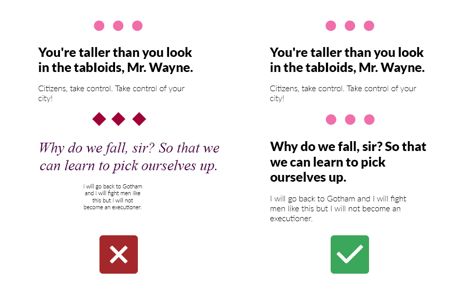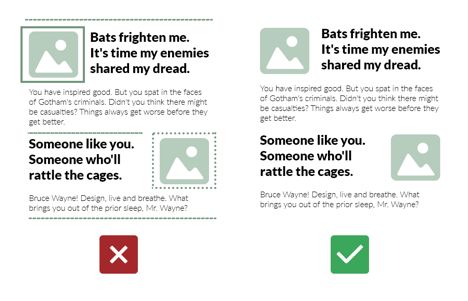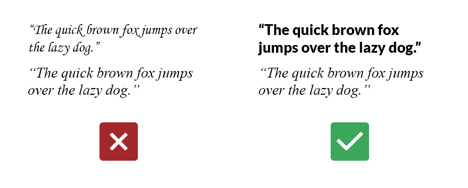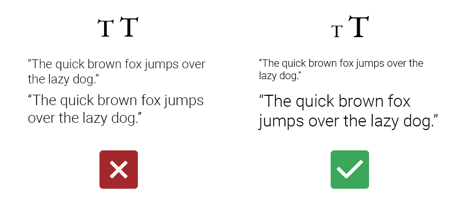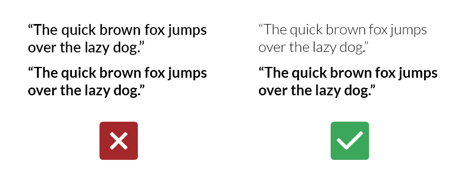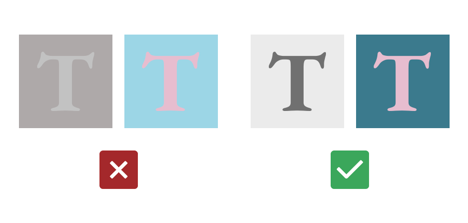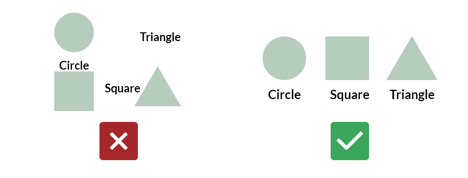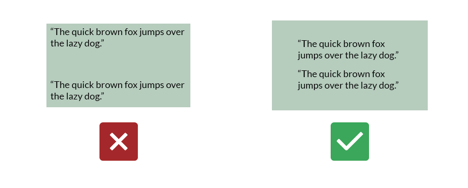
UI设计师必须知道的四大UI设计原则
这些原则来自专业设计师在日常工作中的经验积累、对作品集的分析、Facebook和ins上的设计海报、油管上的短视频等等。
很多朋友问我,怎么做才能让设计出来的东西看着会更好呢?俗话说得好“授人以鱼,不如授之以渔”,所以比起直接帮你们设计,我更愿意告诉你们一些有价值的设计原则,这样的话,当你们再遇到同类问题时,你们可以运用这些原则更好的解决问题。时间长了,我发现我一直在给设计师们重复的建议,于是我总结出了以下四个UI设计法则。
对比
♦ 确保所有元素之间有足够的对比   ♦
为什么呢?因为有些设计元素之间只有一点点不同,在差异极小的时候,很容易形成一种类似恐怖谷的感觉。看起来总是觉得不太舒服、难以理解,这肯定不是我们想要的效果,所以设计元素要么完全相同,要么明显不同。
1、颜色:
深色文字用在浅色底上,反之亦然
例:不要把浅灰色放在中灰色背景上,不要把浅粉色和浅蓝色搭配在一起;这样不仅不便观看,也很不协调
2、尺寸:
将 大小完全相同 或者 大小差异明显 的元素放在一起
例:不要把32pt和36pt的文本放在一起;18pt和36pt文本放在一起会更合适
3、字重:
尺寸相同时,要将 粗细完全相同 或者 粗细差异明显 的元素放在一起
例:不要把某种字体的粗体和黑体放在一起,因为它们看起来太相似了;细体和粗体搭配起来会更好
4、字体样式:不要把两个斜体字(或衬线体)放在一起
例:不要把“Times New Roman”和“Georgia”放在一起,因为它们看起来太像了;要搭配不同风格的字体
一致性
♦ 确保相似的元素表现形式一致  ♦
1、作品通过保持元素的一致性才能保持简洁,应该让用户把注意力集中在设计亮点上,而不是去关注那些无关紧要的东西。
2、一致性会增加用户的信任感,让作品看起来是经过精心设计的,而不是随便拼凑在一起的。(需要注意的地方有:字体,色调,网格,对齐,装饰元素、风格等等)
当你在创作系列作品时,要让它们保持风格一致,比如Youtube的视频展示图,或者Medium的文章封面,设计风格都应该保持一致。换句话说,你的作品需要有你自己的风格。
奥卡姆剃刀原理
♦ 减少视觉噪声  ♦
设计师们总是在强调少即是多。为什么呢?因为人类的大脑的容积是有限的,很难在超负荷的状态下处理信息和做决定,所以简洁的元素更适合大脑接收信息。(元素包括字体、颜色、阴影、结构、笔画、图标、图片等等)
奥卡姆剃刀原理可以应用到所有的事中。
比方说,如果只需要用2个元素就能完成某件事,就不要用3个元素;如果某件事可以用10个元素来完成,就不要用20个!
空间
♦ 事物所处的位置决定了它是否是关键  ♦
为什么位置很重要? 因为元素摆放的位置、元素周围的留白,都会影响设计的复杂性。因此,更好的位置摆放会使产品看起来更加赏心悦目,也更加易于交互。
设计中的空间使用表现在这3个方面:
1、亲密原则=相关性
与其他元素相比,彼此更接近的元素,会被认为存在更多的关联。这个原则很重要,我感觉它常常被专业的设计师忽视。
这个原则有多种实际的案例,例如:
• 行间距应该大于字间距;同样的,段落间距也应该比行间距要更大
• 设计元素之间的间距,应小于这些元素与外部边缘的间距
• 元素的相关说明信息应该位于相关的元素附近
2. 负空间
结合奥卡姆剃刀原则,尽可能的为你的设计提供负空间,使它们看起来更整齐且、意义更明显。如果将太多元素放在有限的空间内,就好像同时听三首歌一样,听到最后什么都听不到。
看看Apple的网站,人们可以非常清楚地了解所表达的内容
3.重要性和秩序
这个原则是非常常见的,但我觉得还是要在这里强调一下!
越重要的元素,越应该放在第一位,或者让它们占据最大的空间;并且用一系列连续的事物来表达出秩序感。
最后
恭喜你!如果你在做所有的设计过程中遵循了以上这些原则,那么按照行业标准,这是一个好作品了。
注释:
1、恐怖谷:恐怖谷理论是关于人类对机器人和非人类物体的感觉的假设;其说明了当机器人与人类相似程度超过一定程度的时候,人类对他们的反应便会突然变得极其反感恐惧。本文中所使用的恐怖谷说法是形容设计中元素之间有极高的相似度,让用户产生不舒适感。
2、奥卡姆剃刀定理:这个原理称为“如无必要,勿增实体”,即“简单有效原理”。